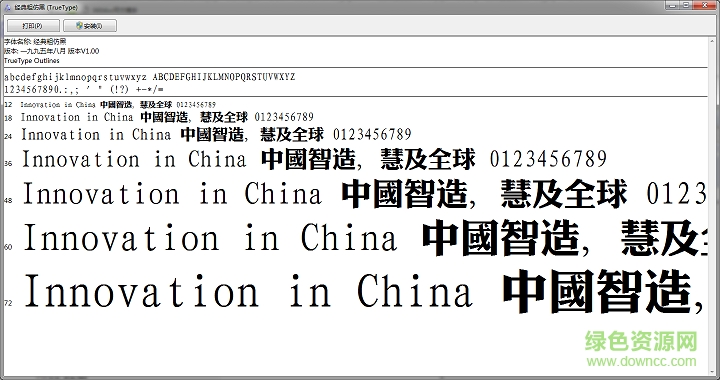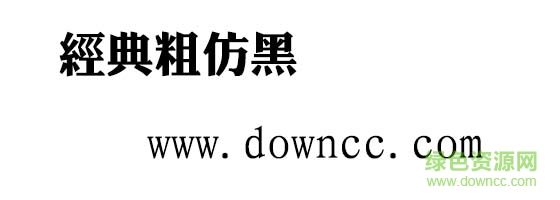
經(jīng)典粗仿黑是一款粗黑的中文繁體字。很多朋友在找經(jīng)典粗仿黑簡體,其實該字體是沒有簡體的,本身就是繁體,不需要在去尋找簡體了。趕快來綠色資源網(wǎng)下載吧!
1.中國的字體設(shè)計是在印刷術(shù)的產(chǎn)生和發(fā)展中應(yīng)運(yùn)而生的。在古代,中國的字體設(shè)計曾有過輝煌的歷史時期,在宋朝時進(jìn)入黃金時代。
2.清朝末年,鉛字排版印刷術(shù)傳入中國,字體設(shè)計進(jìn)入鉛字時代。這個時期的字體設(shè)計既要帶有傳統(tǒng)文化的審美慣性,又要符合鉛字印刷的工藝要求,字體設(shè)計走到了轉(zhuǎn)折的關(guān)口。
3.鉛字印刷是印刷走入機(jī)械化、工業(yè)化時代的標(biāo)志,但在這一時代里,印刷字體設(shè)計卻始終無法超越手工勞動的制約,無法擺脫刻模、鑄字、撿字、排版等一系列印前繁雜工藝的束縛